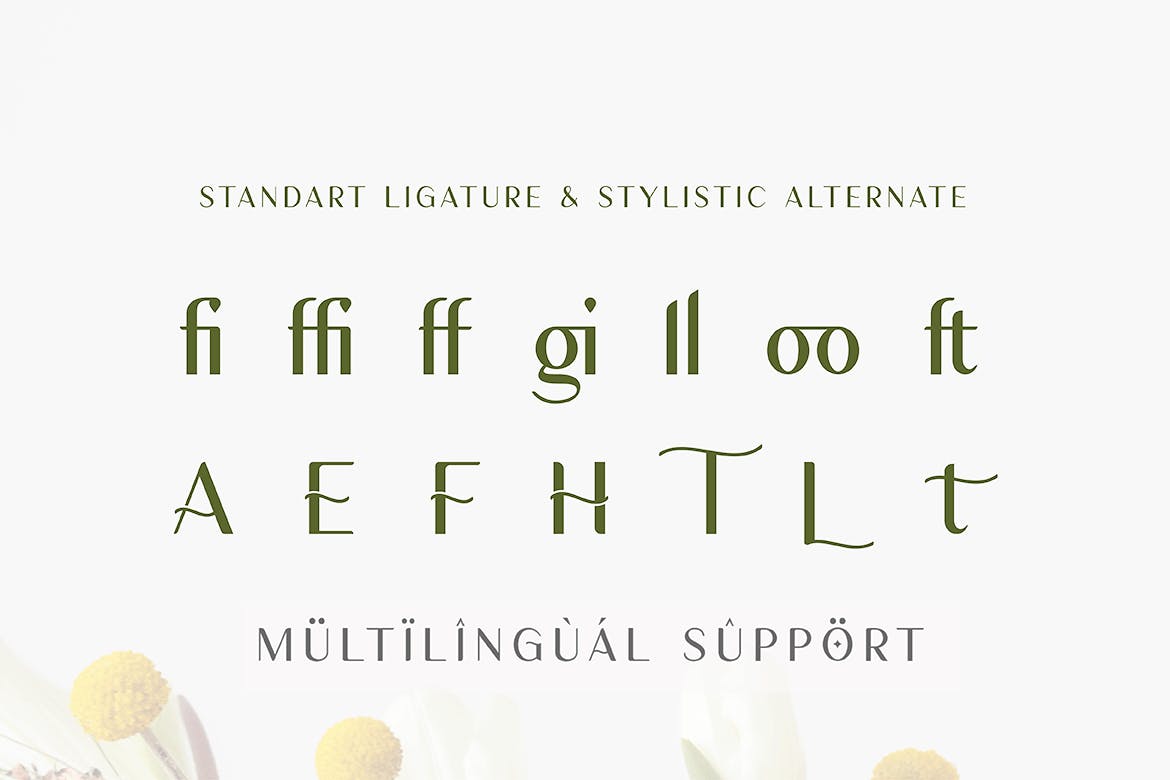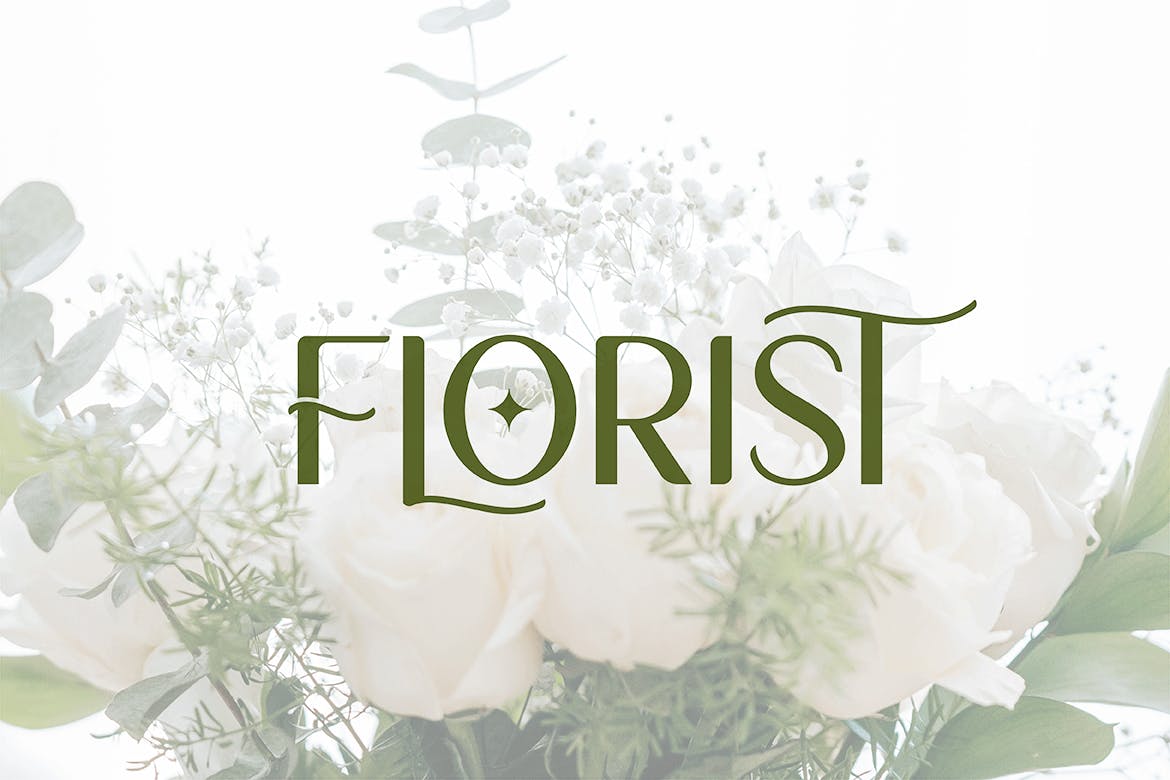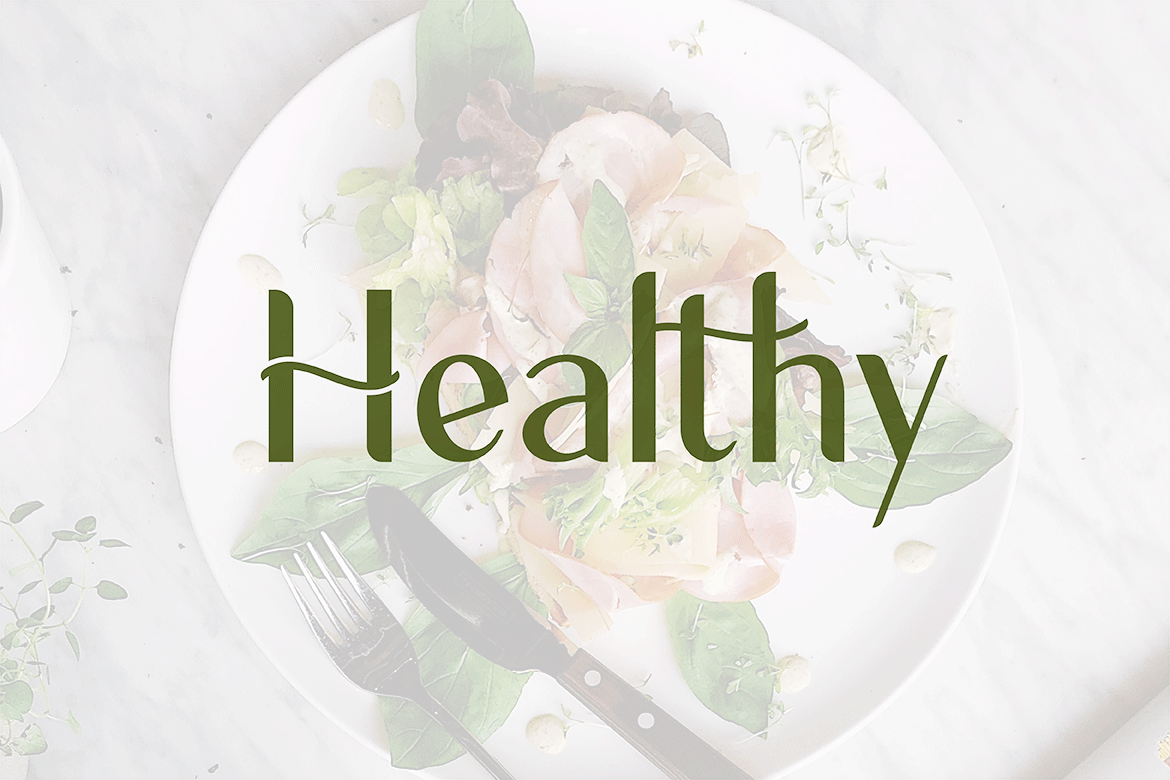
Luxury Sans Serif Font
فونت لافوگل لوکس با طراحی بینظیر و مدرن مناسب برای پروژههای طراحی شما.
فونت لافوگل لوکس سانس سریف
حروف بزرگ
حروف کوچک
اعداد و نشانهگذاری